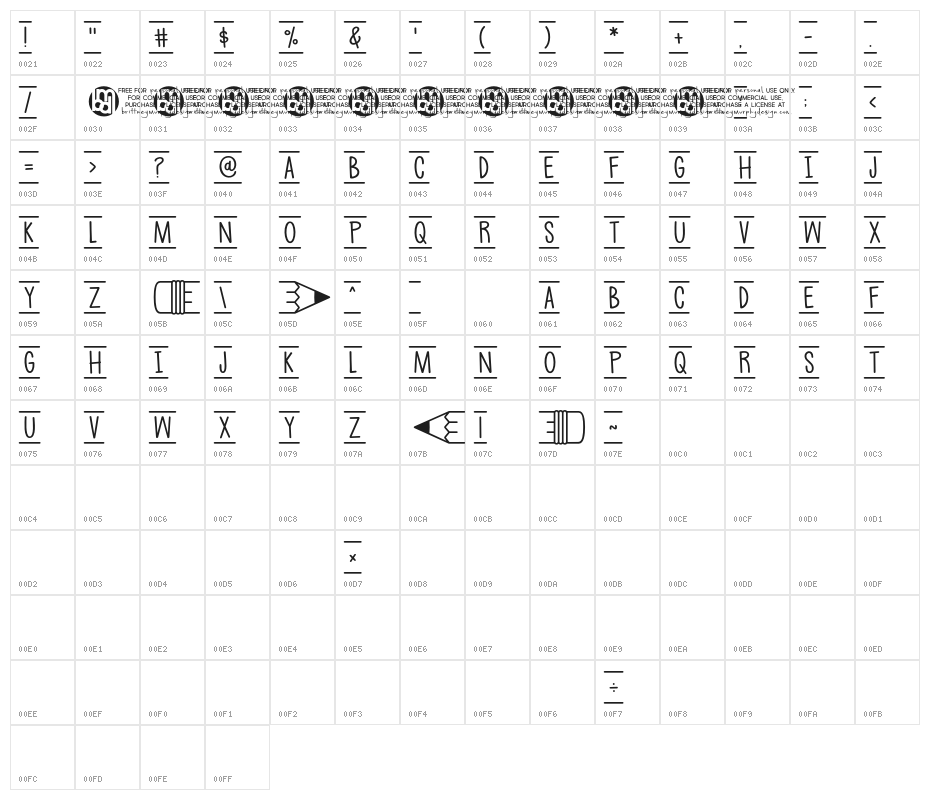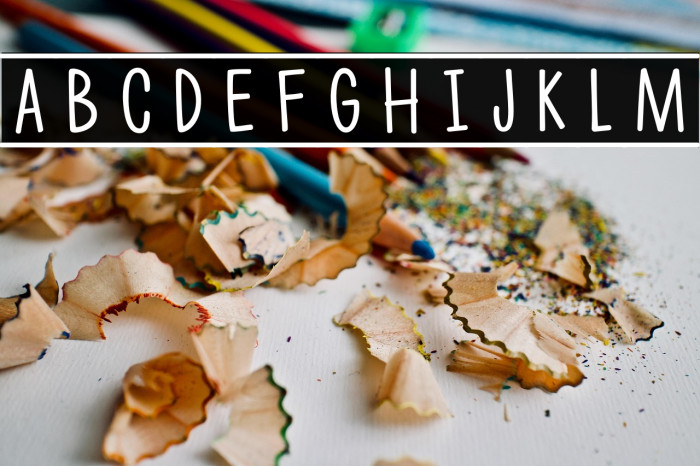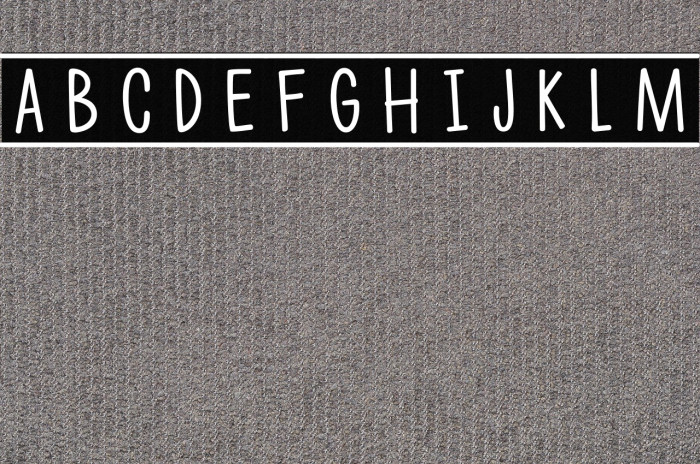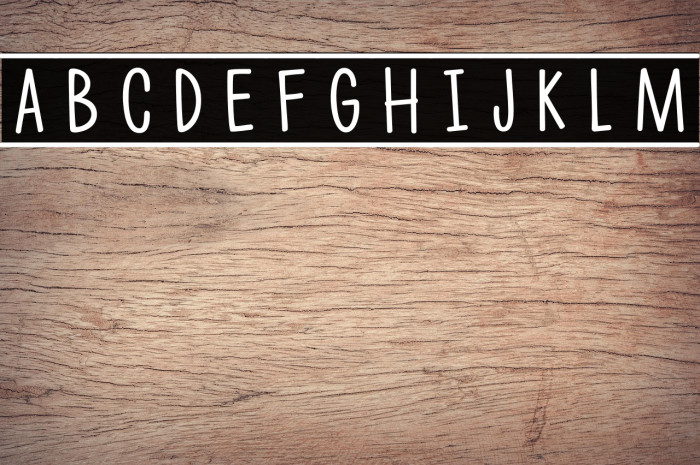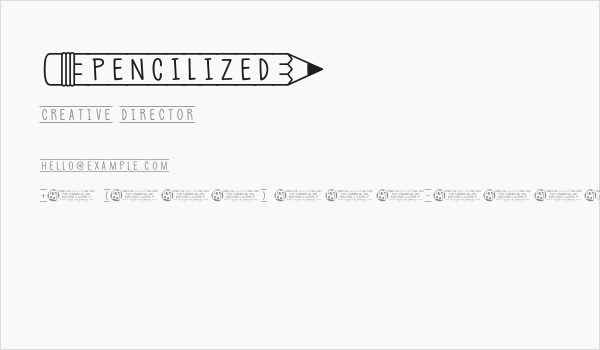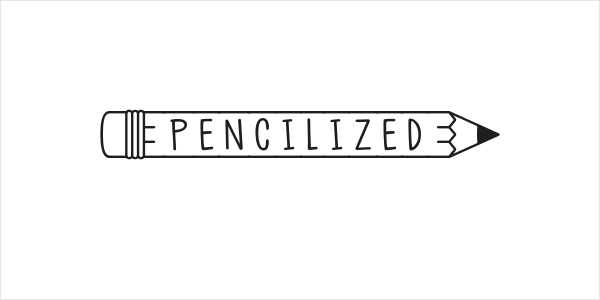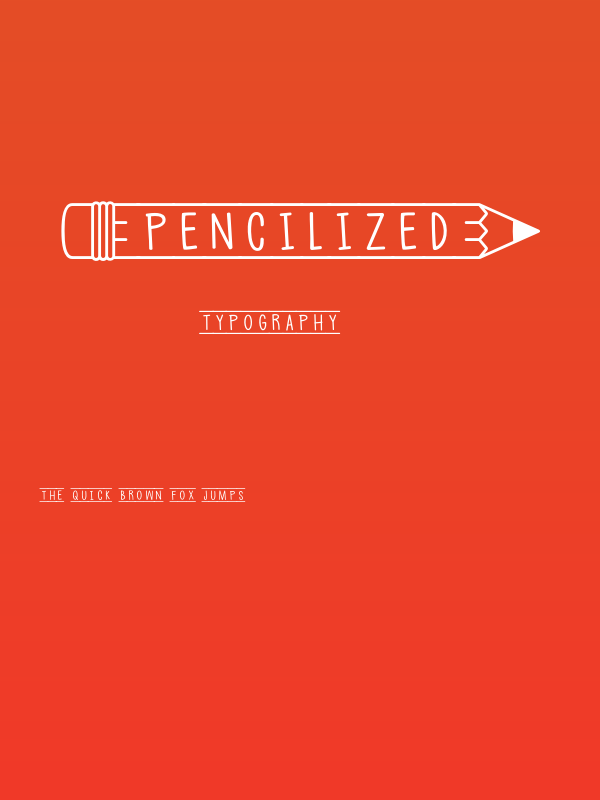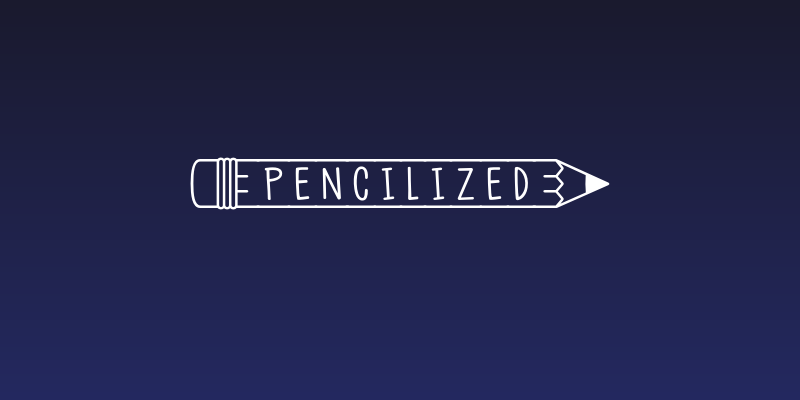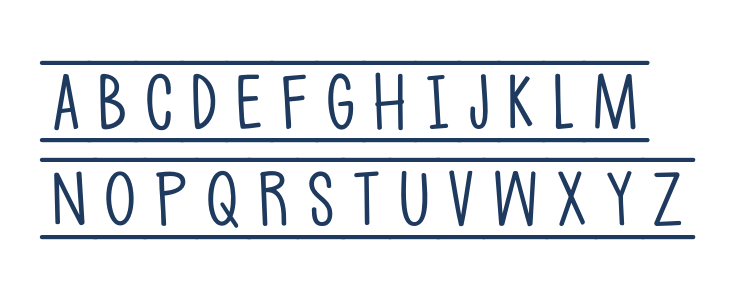
[Pencilized] Font
| Stile generale | Casual |
| Caso d'uso | Headlines, Informal text, Creative projects |
| Progetti proposti | Ideal for children's books, casual invitations, personal notes, and creative projects that require a friendly and approachable look. |